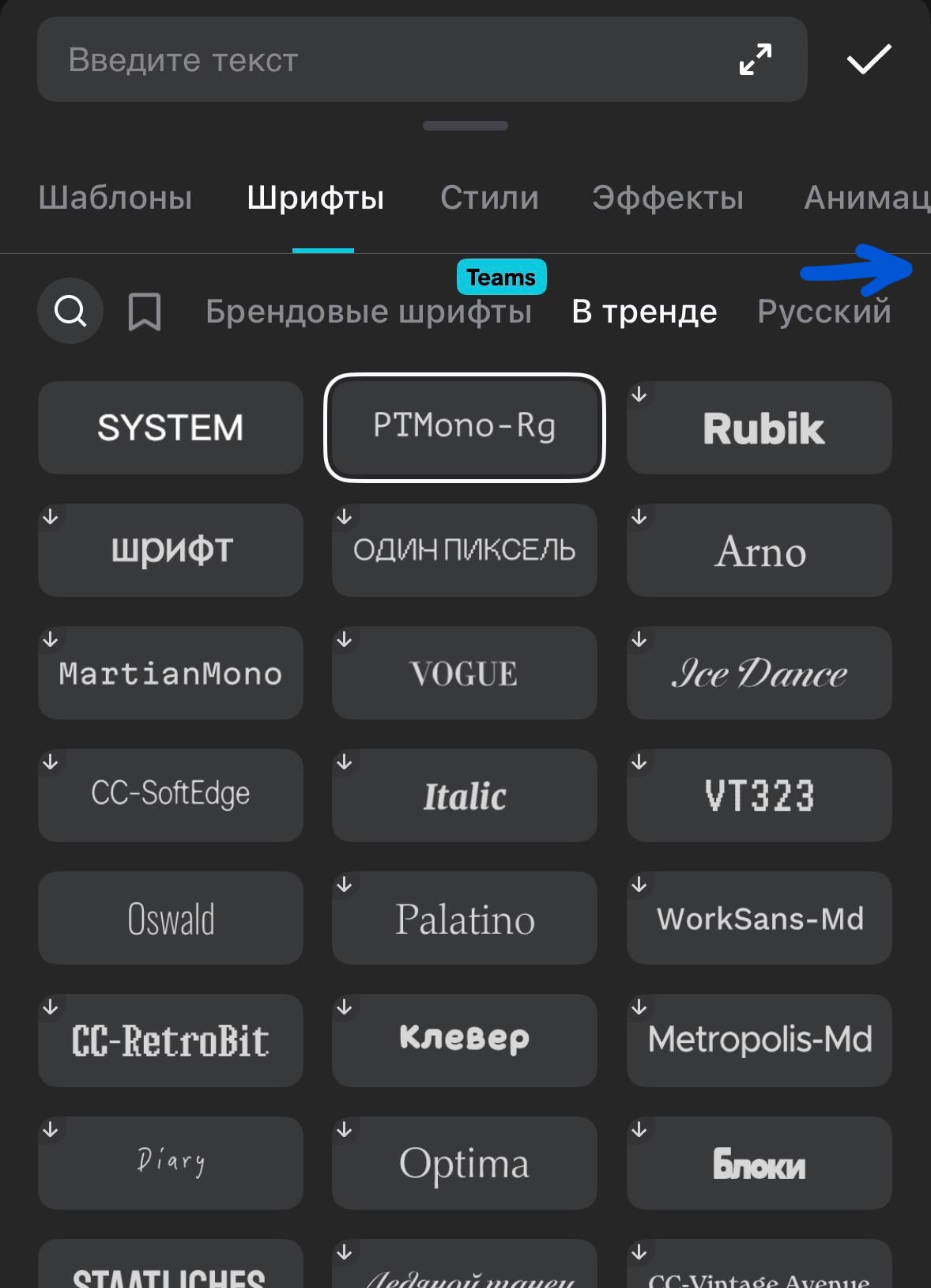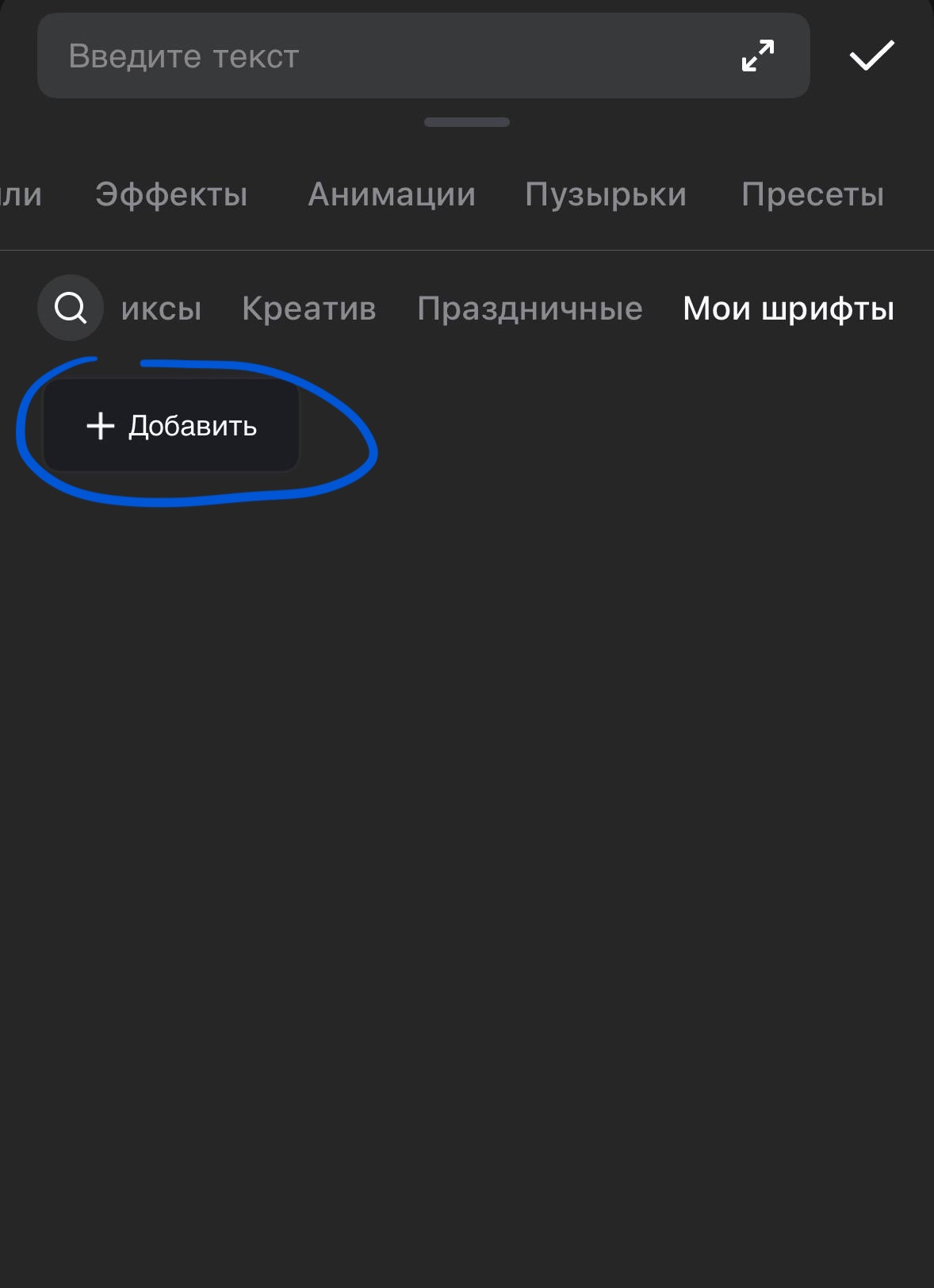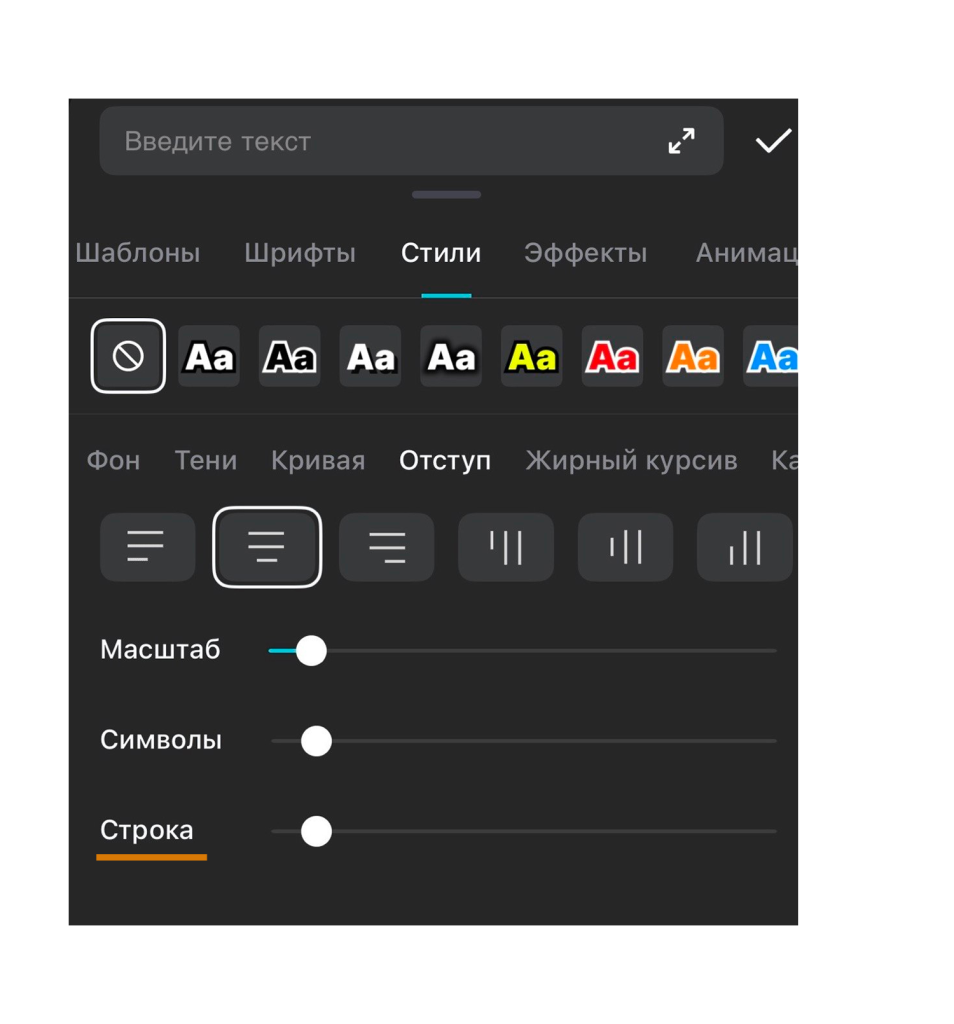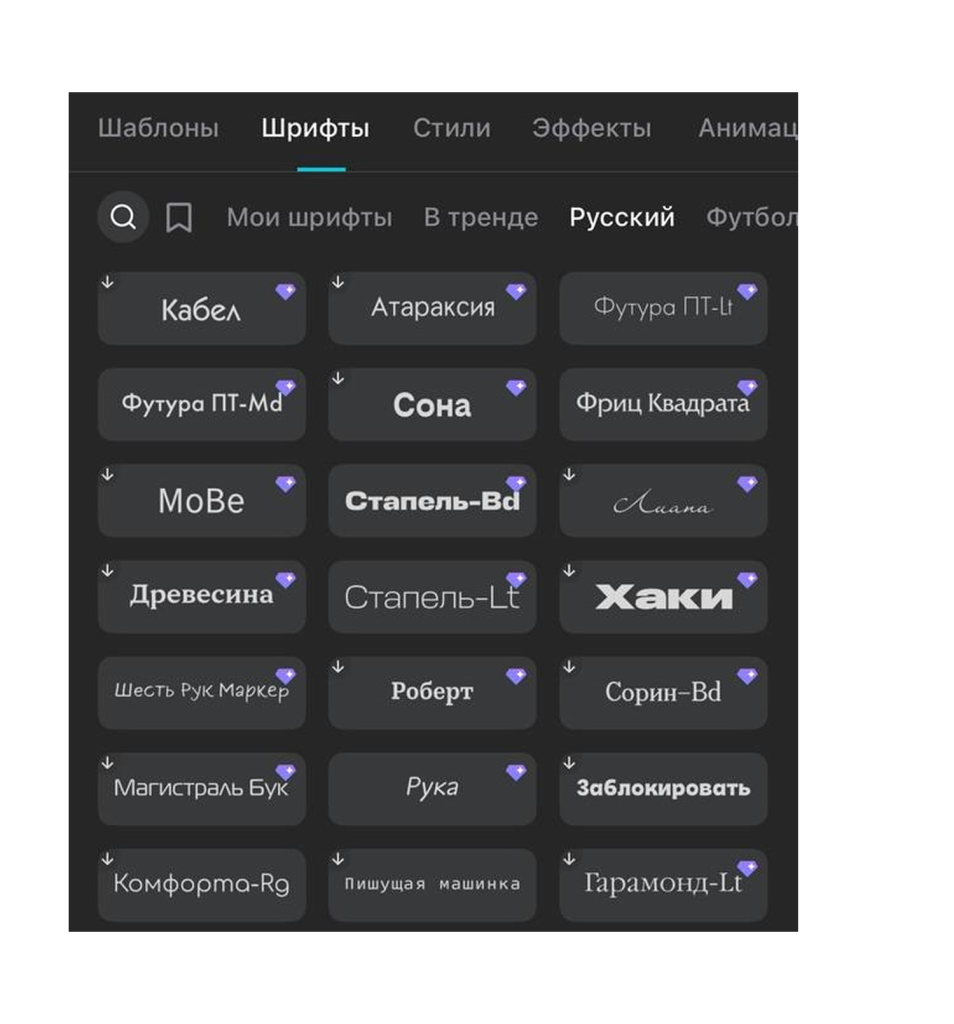
Выбираем шрифт для CapCut: гид от шрифтовой студии
Если нужны шрифты для CapCut, шрифты для Капкута, шрифты для кап капа и куте кута, и для всех прочих вариаций названия — вам сюда •ᴗ•
Возможно, вы слышали, что от шрифта зависит, насколько легко люди смогут прочитать ваш текст, и что шрифт помогает создать нужное впечатление. Но как выбрать читаемый шрифт для видео? И как подобрать шрифт под идею аккаунта?
В начале статьи как раз расскажем о фундаментальных принципах выбора шрифта и покажем подборку шрифтов с отличным дизайном кириллицы. То есть, если вы набираете текст на русском, они вам как раз подойдут. Эти шрифты уже есть в CapCut и их не нужно подгружать откуда-то ещё.
В конце поговорим о технической части: как добавлять свои шрифты в CapCut, если всё-таки хочется, и где искать бесплатные легальные шрифты.
Выбираем шрифт для видео для личного или корпоративного блога
Совет 1. Смотрите на длину текста
Тексты используются в дизайне для разных целей. Одни — чтобы привлечь внимание и передать эмоцию (чаще всего речь идёт о сверхкоротком тексте в 1–2 слова). Другие — чтобы передать информацию читателю: в инструкциях, описаниях или для какой-то важной мысли. Третьи — чтобы юристы не придирались •ᴗ• Это разнообразные дисклеймеры, маркировки рекламы и тому подобное.
шрифт Spile, нечитаемая надписьНейтральный PT Sans (доступен в CapCut без подписки) и Spile, который прекрасно смотрится в крупных заголовках, если хотите, чтобы их читали, и в маркировках, если НЕ хотите, чтобы их читали •ᴗ•
Как и тексты, шрифты тоже нужны для разных целей. Если смотреть на все шрифты мира с точки зрения «для чего они сделаны», то их можно распределить по очень длинной оси координат.
На одном конце оси будут самые скучные «обычные» шрифты — они нужны для того, чтобы человеку было удобно читать много текста. Если шрифт такого типа хорошо сделан, то его вообще никто не замечает, потому что он идеально передаёт информацию и не мешает читателю читать.
А на другом конце оси будут самые яркие, безумные, эмоциональные шрифты, для которых слово из пяти букв — уже слишком длинное. Такой шрифт будет сам работать как иллюстрация и дополнять смысл очень короткого текста своим характером.
текстовый шрифт, читаемый шрифт, универсальный шрифтШрифты с явным характером Mojito/Мохито и Stapel/Стапель доступы в CapCut
*В статье будем приводить названия и на латинице, и на кириллице, потому что в CapCut встречаются оба варианта
Когда вы монтируете в видео какой-то текст, в первую очередь задайте себе вопрос: мне сейчас надо передать информацию (например, вы добавляете к видео текстовую инструкцию для тех, кто смотрит без звука) или мне сейчас надо добавить к тексту эмоциональности?
Часто ответ на этот вопрос помогает найти ещё и длина текста: если у вас одно короткое слово, можно выбирать яркий странный шрифт, а если 5–6 строчек, то логично, что шрифт должен быть из более «обычной» части спектра.
Кратко
1. Смотрите на длину текста и вашу задачу.
2. Для заголовка, выделения, пары слов на экране — можно брать более яркий шрифт, как Mojito/Мохито, Six Hands/Шесть рук, Krok/Крок.
3. Если у вас субтитры или много текста в ролике, то лучше обратить внимание на достаточно нейтральные шрифты. При этом не обязательно, чтобы они были совсем без характера: Futura PT/Футура ПТ или Stapel/Стапель тоже отлично подойдут.
4. Если нужно, чтобы шрифт ни на секунду не привлёк к себе внимания и не добавил эстетики, а только быстро и чётко передавал информацию — посмотрите в сторону нейтрального PT Sans/ПТ Санс*
Конечно, эти же принципы подойдут и для карточек в карусели.
*Все перечисленные шрифты есть в CapCut, но некоторые доступны только по подписке
Читайте также: Как выбрать универсальный шрифт
Совет 2. Не злоупотребляйте характером шрифта
Кому-то может показаться, что текстовые, хорошо читаемые шрифты — скучные. В каком-то смысле так оно и есть, но если наша задача — дать зрителю инструкцию, рецепт, полезный совет, точное описание продукта,— то «скучный» шрифт справится с этой задачей гораздо лучше, чем весёлый. Лучше меньше дизайна, чем больше.
Pragmatica Next, текстовый шрифт, Ден @donroach, курс Кирилла Пестовского
Pragmatica Next — нейтральный шрифт без засечек, жемчужинка швейцарской типографики. Да, это не шрифт с красивыми завитками, но зато всё читается. Автор злободневной анимации — Ден @donroach с курса Кирилла Пестовского по моушн-дизайну
4. DIN Condensed
5. Engravers Gothic
6. Friz Quadrata
7. Futura PT
8. ITC Bauhaus
9. ITC Garamond
10. ITC Kabel
11. Krok
12. Laguna
13. Liana
14. Magistral
15. Mojito
16. Motter Tektura
17. Rodchenko
18. Six Hands
19. Stapel
20. PT Sans
21. PT Mono